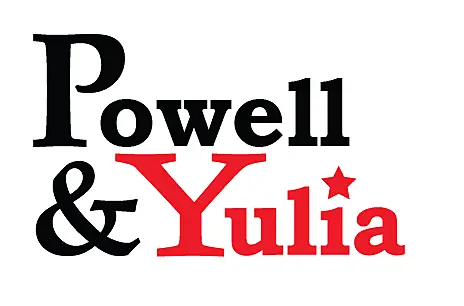
Помогите распознать шрифт
Ищу целый день по всем возможным ресурсам, не совпадает ничего :(
Цитата Evilis:
Вот тут распознавать шрифт по картинке (загружаем свой пример). Результат разумеется не всегда на 100%, но частенько очень выручает.
была уже, нет совпадений :(
полного совпадения нет, буквы P и Y  не такие
Мне кажется сейчас существует уже такое количество шрифтов, что похожих просто немерено.
Цитата soskan:
Заглавные в кореле кривыми можно обвести и пользоваться